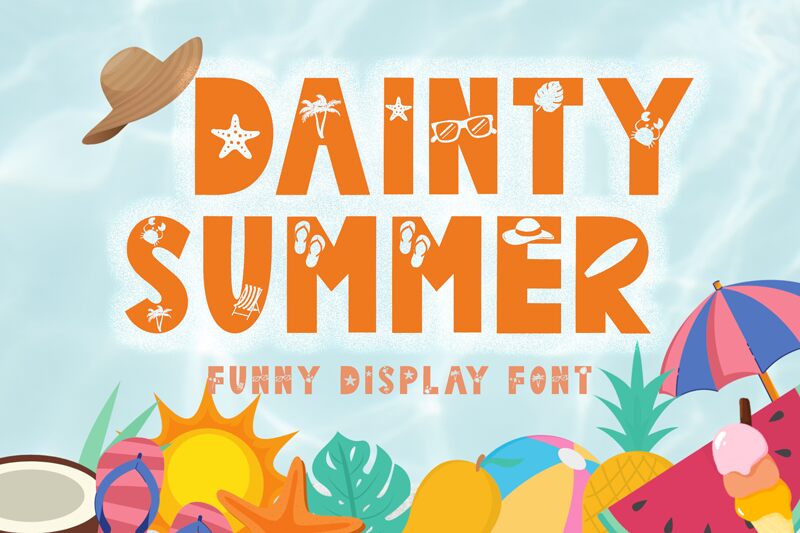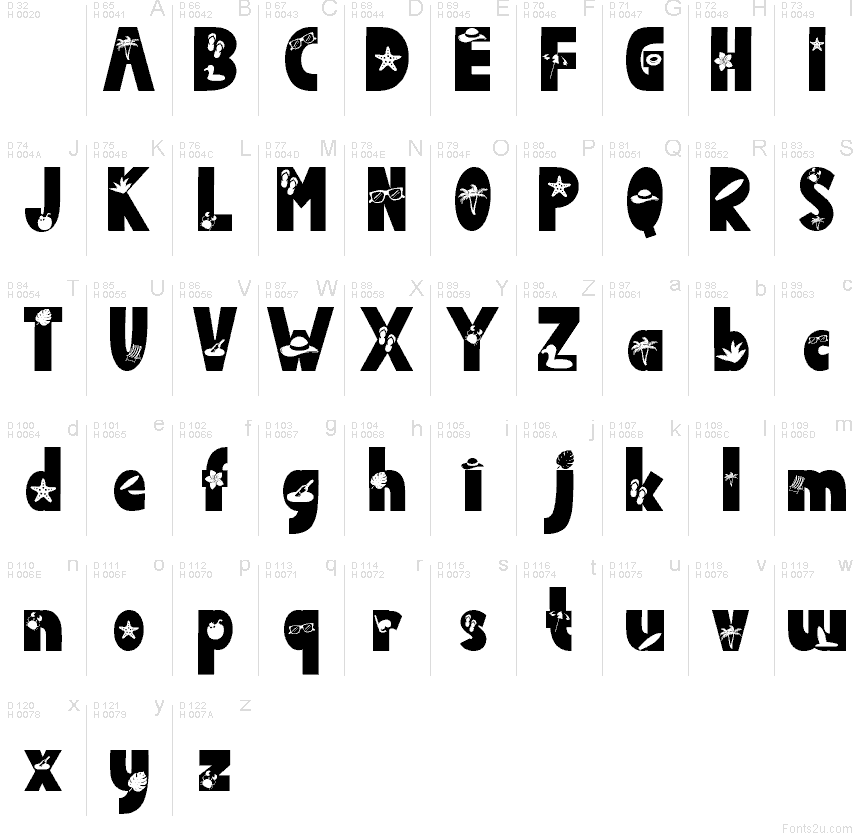
Dainty Summer
Dainty Summer de Yoga Letter es una tipografía display gratuita de temática veraniega, con letras redondeadas y pequeños motivos vacacionales integrados en el diseño. La familia incluye formas como estrellas de mar, palmeras, un sombrero de playa y un pequeño cangrejo, lo que le aporta un toque costero muy definido sin resultar recargada.
Dainty Summer funciona de maravilla en invitaciones a fiestas playeras, branding para resorts, carteles de viajes, banners de rebajas estacionales, flyers de eventos y creatividades desenfadadas para redes sociales. Es ideal para proyectos que buscan un toque de relax vacacional, ya que sus formas decoradas transmiten el tema por sí solas, dejando suficiente espacio para textos cortos y llamativos.